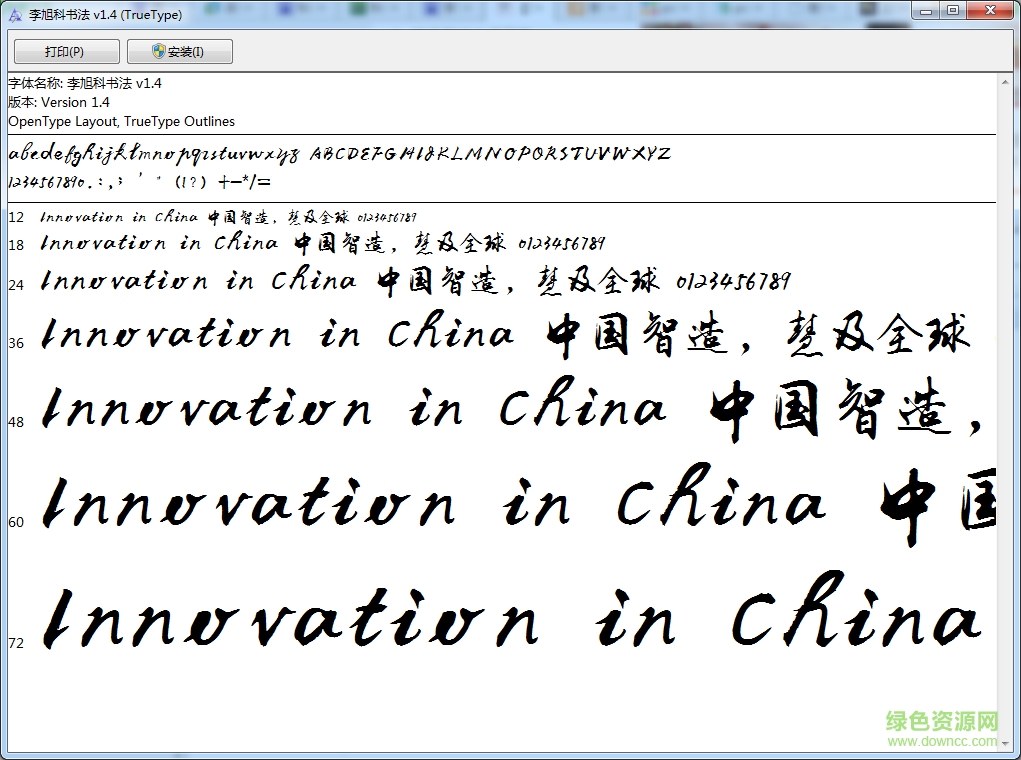
李旭科书法v1.4是一款非常好用的书法字体,字体粗细适中,广泛应用于美工设计、图文印刷、海报宣传等多种行业,使用简单时刻彰显个性。快来绿色资源网下载体验吧!
李旭科书法v1.4介绍
李旭科书法是书法家李旭科书写的一套字体,字体飘逸,适合喜欢书法的朋友临摹研究,也适合广告、网页等设计人员用作字体设计;需要的朋友不要错过。